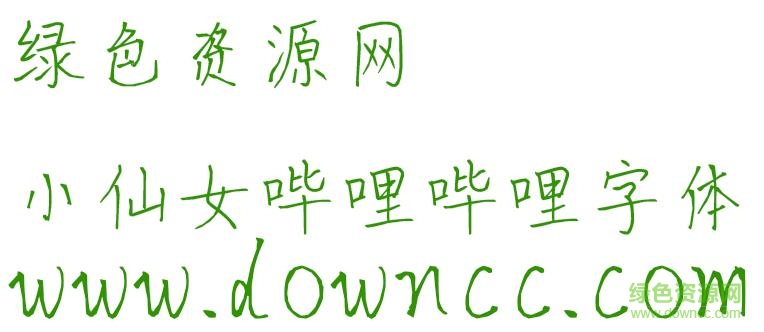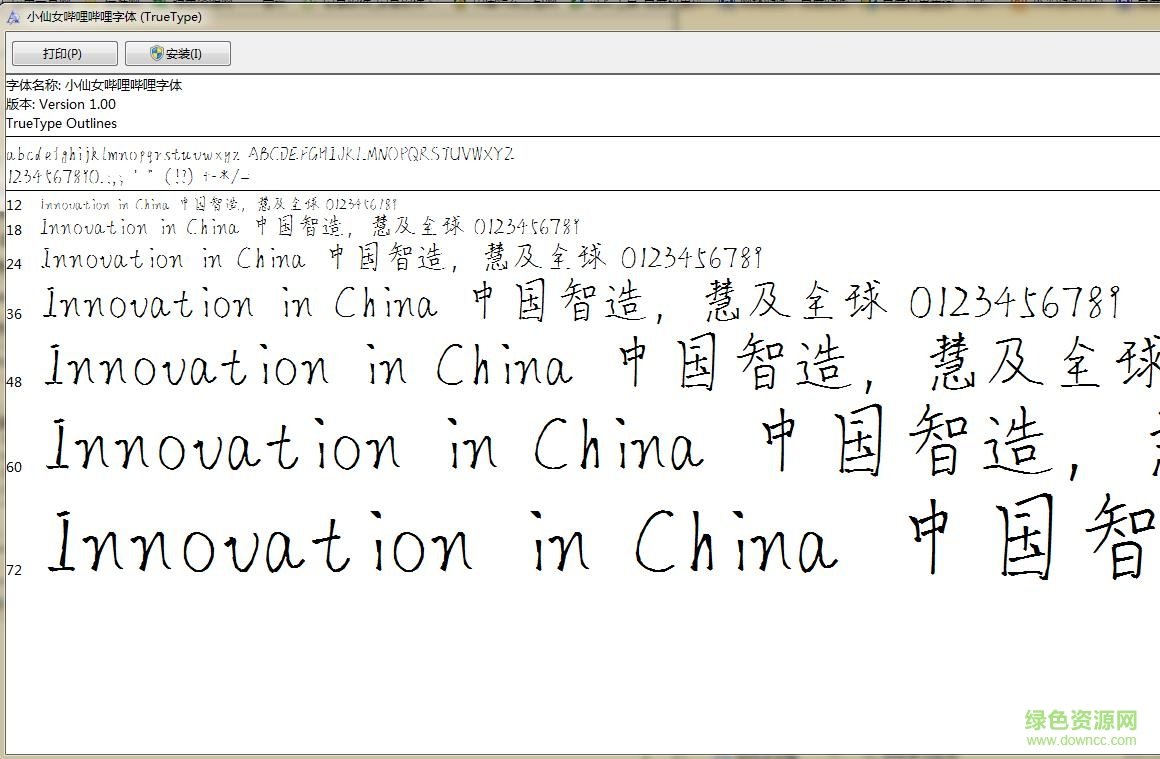
小仙女嗶哩嗶哩字體ttf的字體樣式就像仙女一樣十分好看,這款字體在可以在聊天的時候用看著很不錯的,而且在字體輸入的時候也有一種十分不錯美感!
在使用這款字體的時候感覺這款自己的名稱十分有趣,而且字體使用后覺得非常不錯的,我一般用戶來做藝術(shù)字,可以獲得很好的顯示效果!更多字體可以在綠色資源網(wǎng)檢索下載哦!